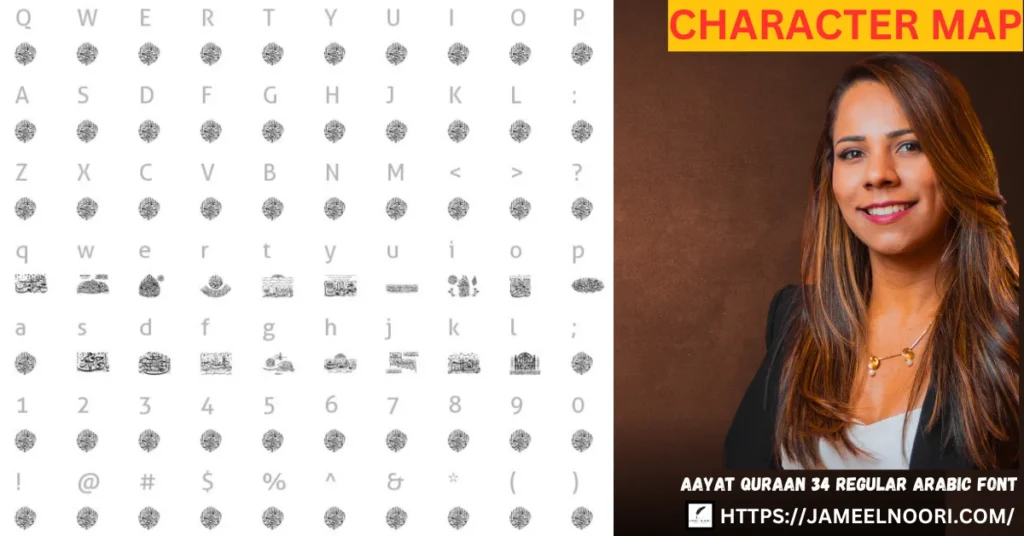
Introduction to Aayat Quraan 34 Regular Arabic Font
Aayat Quraan 34 Regular Arabic Font Pakistan me designers aur calligraphy lovers ke liye ek popular choice hai. Yeh font apne clean aur readable style ke liye jana jata hai. Is font ka use Quranic text aur Arabic typography projects me widely kiya jata hai. Is article me hum apko is font ke bare me complete information dy gy taki aap bina time waste kiye is font ka best use kar saken.
Features of Aayat Quraan 34 Regular
Aayat Quraan 34 Regular font ke kuch khas features ye hain:
- Clean aur easy-to-read design
- High-quality Arabic calligraphy
Ye features is font ko best Arabic font banate hain Pakistan aur Lahore, Karachi designers ke liye.
Why Choose Aayat Quraan 34 Regular Arabic Font
Agar aap Arabic fonts aur Urdu fonts ke shaukeen hain to Aayat Quraan 34 Regular aapke liye ideal hai. Is font ko choose karne ke reasons ye hain:
- Professional and readable typography
- Perfect for digital and print projects
- Easy integration with design software
Compatibility and Usage Tips
Aayat Quraan 34 Regular Arabic Font har design project ke liye suitable hai. Kuch tips:
- Digital publications: Easy readability on screens
- Print materials: High-quality calligraphy for posters & books
- Urdu & Arabic fonts: Can be combined for multilingual designs
Design Ideas Using Aayat Quraan 34 Regular
Yeh font designers ko creative freedom deta hai. Kuch ideas:
- Quranic calligraphy projects
- Islamic greeting cards
- Social media posts in Urdu & Arabic
- Logos aur branding for Islamic businesses
Advantages Over Other Arabic Fonts
Aayat Quraan 34 Regular other Arabic fonts se better hai kyunki:
- Clean aur professional appearance
- Easy customization
| Feature | Aayat Quraan 34 Regular | Other Fonts |
| Readability | Excellent | Good |
Best Practices for Using Aayat Quraan 34 Regular Arabic Font
- Maintain proper line spacing for readability
- Use for headings and body text as needed
- Combine with Urdu fonts for multilingual content
- Avoid overuse to keep design clean
Aayat Quraan 34 Regular Arabic Font Pakistan ke designers aur Urdu/Arabic calligraphy lovers ke liye ek excellent choice hai. Is font ko download aur install karna bohot easy hai, aur iska clean design har project me professionalism add karta hai. Agar aap Urdu fonts aur Arabic fonts me interest rakhte hain to yeh font apke liye ultimate guide ke sath perfect hai.
FAQs about Aayat Quraan 34 Regular Arabic Font
What is Aayat Quraan 34 Regular Arabic Font?
It is a Regular TrueType Arabic font suitable for Quranic texts and design projects.
Can I use this font in Urdu projects?
Absolutely, it blends well with Urdu fonts and bilingual designs.
Can I use it for print materials?
Yes, it is perfect for high-quality print projects like posters and books.